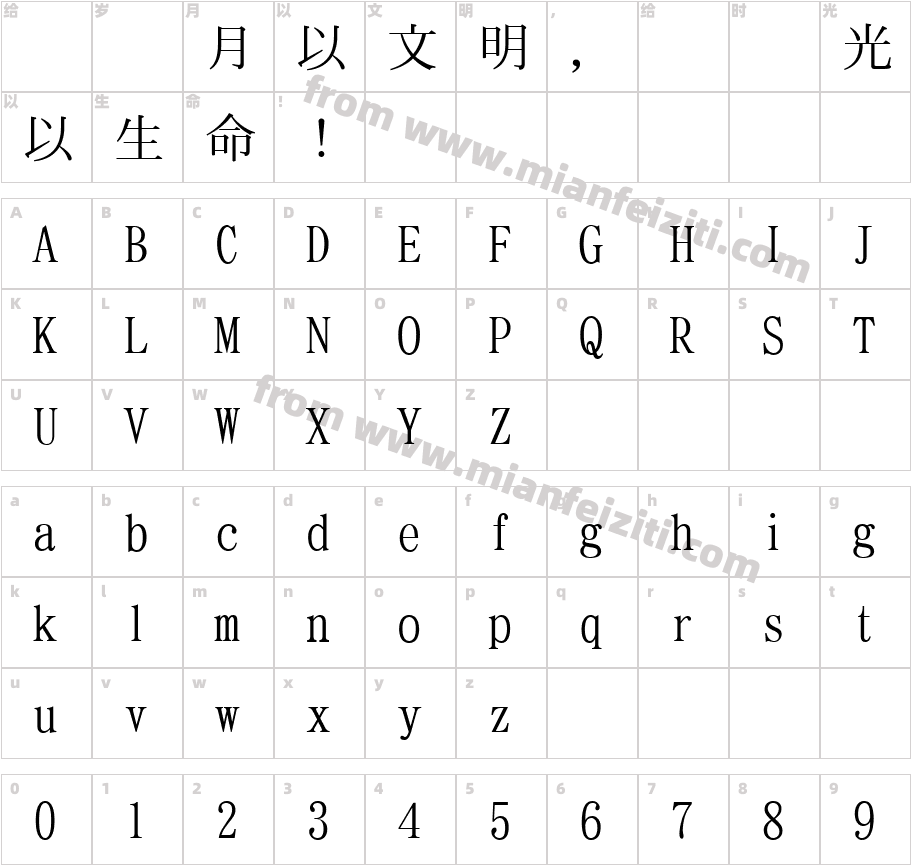
T明朝
字体名称: T明朝
T字体是由东京大学大学院情报学环·学际情报学府坂村·越冢研究室的跨学科信息研究研究生院维护的大型汉字字体。它由3种TrueType字体,由明朝体、黑体和楷书组成,用于120,000个汉字字符集。120,000个字符的汉字集包括列入“Daikan-WA辞典”(由Daishukan书店出版)由良治诸桥和“康熙字典”字,名称和地名清朝中国。的康熙皇帝编译GT字符大约80,000个字符集,包括汉字,其中包括基于中国宋明时代文学作品中提取的宋明变体字符集大约35,000个字符,以及经典中使用的中国青铜铭文。包括从句子中提取的字符。
结果,我们朝着缺乏汉字字体的问题迈出了一大步,这一直是东亚地区文档信息处理中关注的问题,而在现代日本,每天使用的所谓变体字符问题就是这是一个非常罕见的例外,它不仅几乎可以解决,而且还是可以承受中文书籍(中国古典文学)数字化的字符集,并且是支持东方文化研究的学术基础。
T字体的整体图如下所示。由于字符数量巨大,我们将按照完成各种维护工作的顺序将其发布给公众。这次,我们将发布Mincho,Gothic和适用于Windows和TRON格式的GT字符集的常规脚本的TrueType字体。